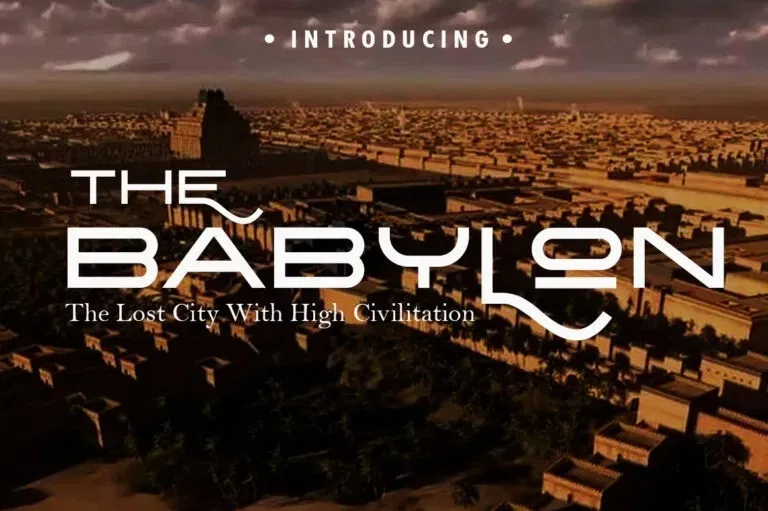
Babylon Font
A Babylon Font é uma nova escolha para designers que procuram um estilo clean e moderno sem perder a elegância. Inspirada no universo do 99designs, onde Hanken Studio criou esta fonte sofisticada, ela se destaca como uma opção perfeita para projetos de marca, headlines e embalagens de produtos. Com seu aspecto clássico moderno, a Babylon Font é ideal para adicionar um toque único a seus trabalhos gráficos. Perfeita tanto para uso em materiais impressos quanto online, esta fonte sans serif se assegura de que sua mensagem seja fácil de ler e atraente ao mesmo tempo. Seja você um profissional ou iniciante na arte da design gráfico, não deixe de experimentar o encanto desta fonte elegante e moderna para aumentar a qualidade visual de seus projetos.